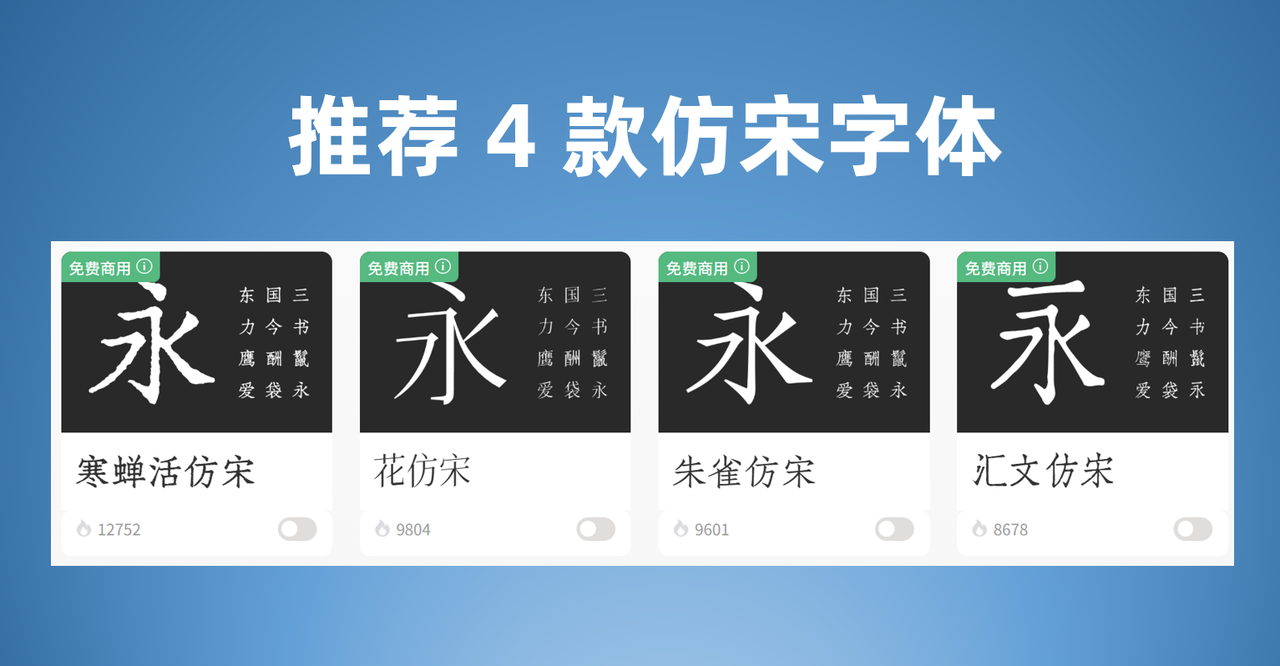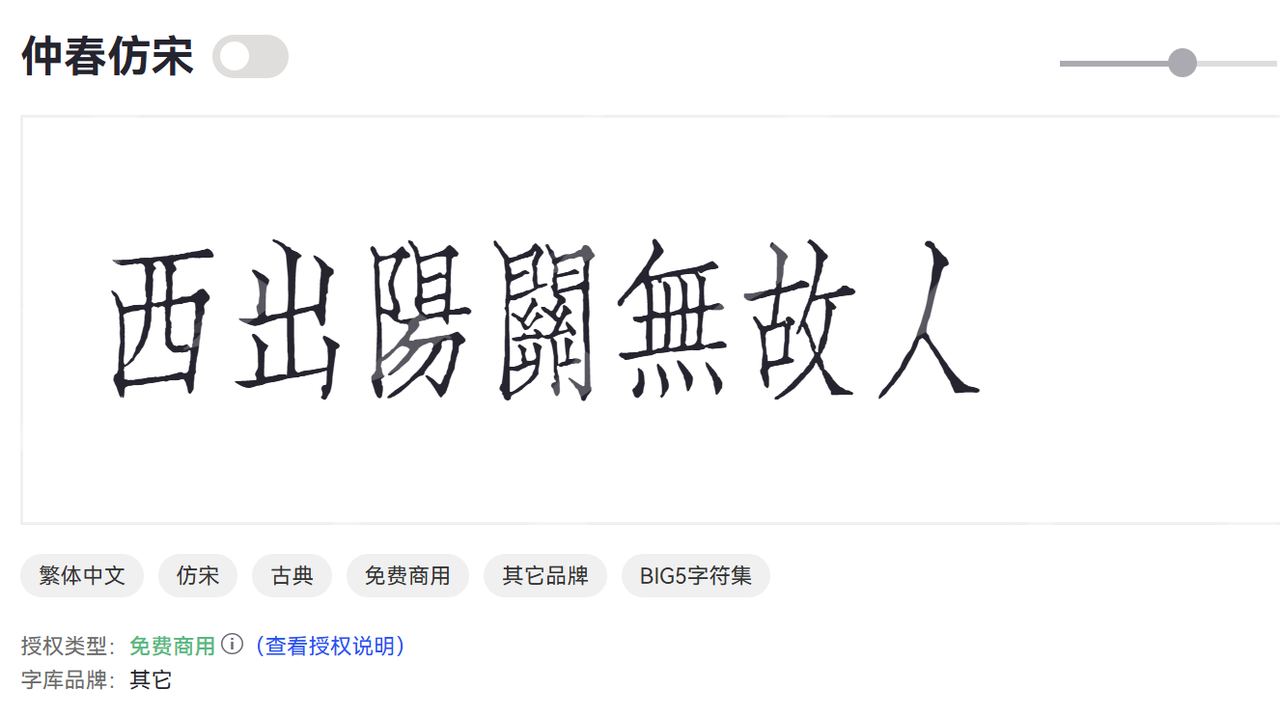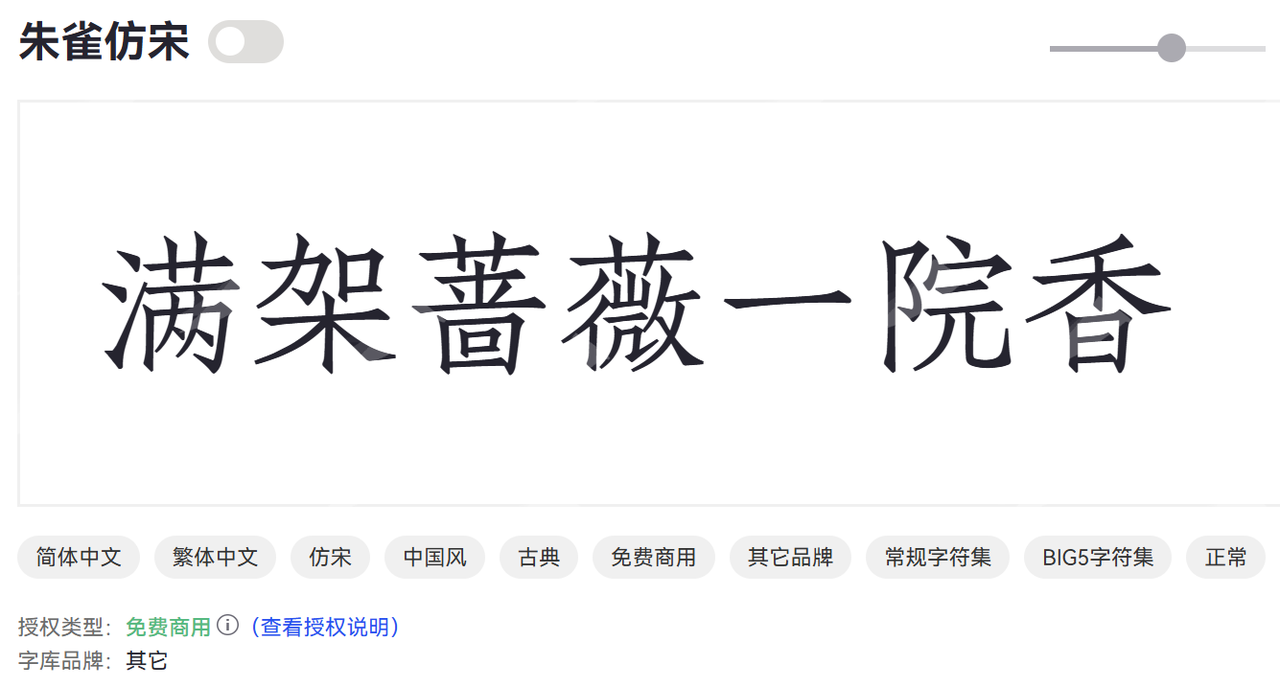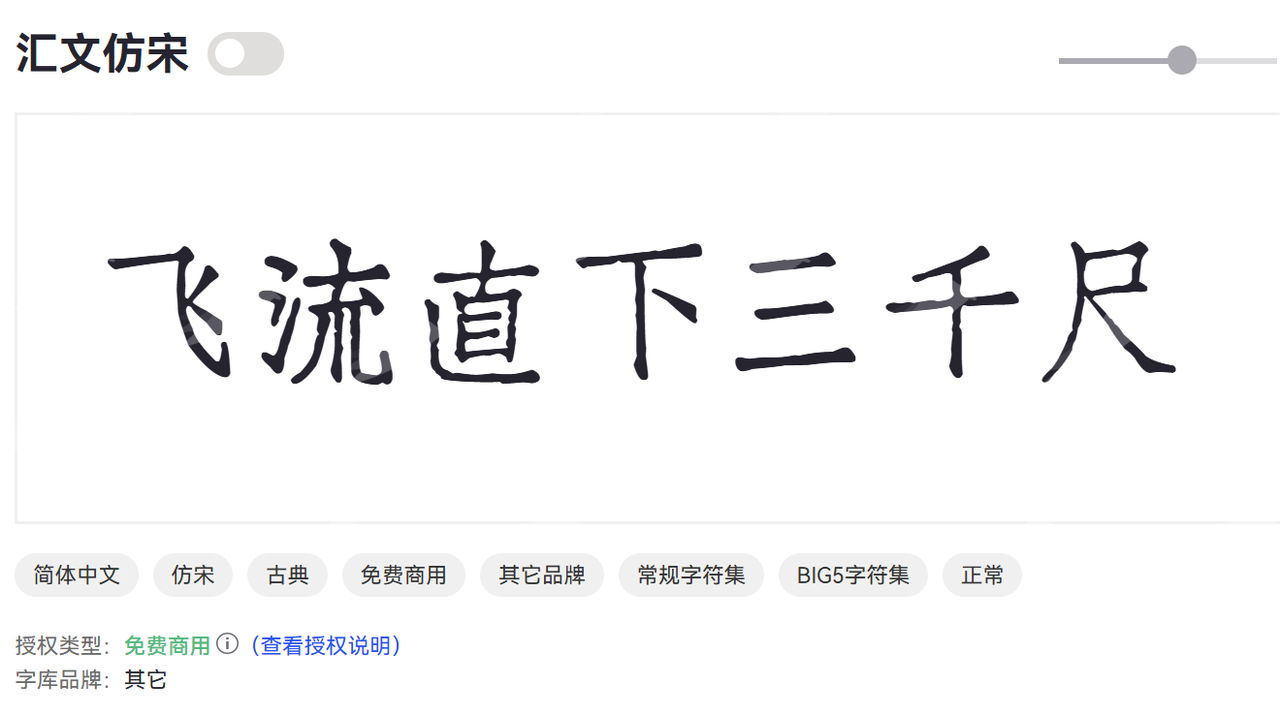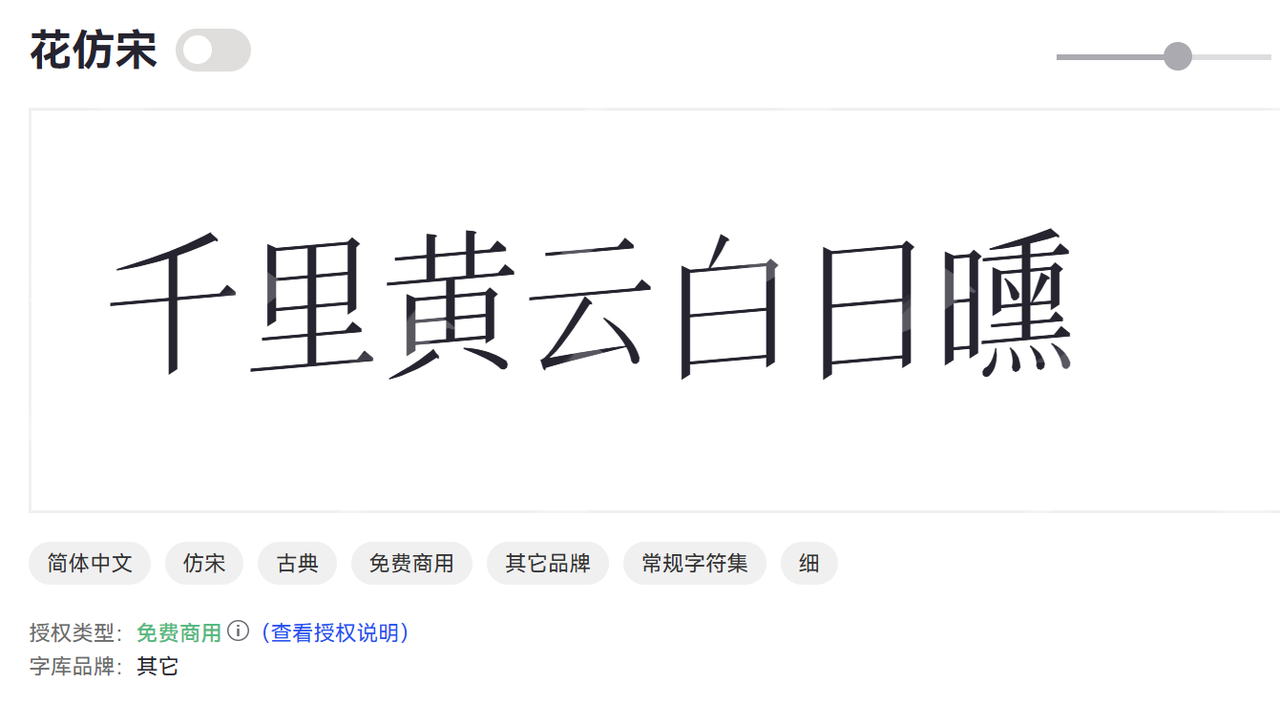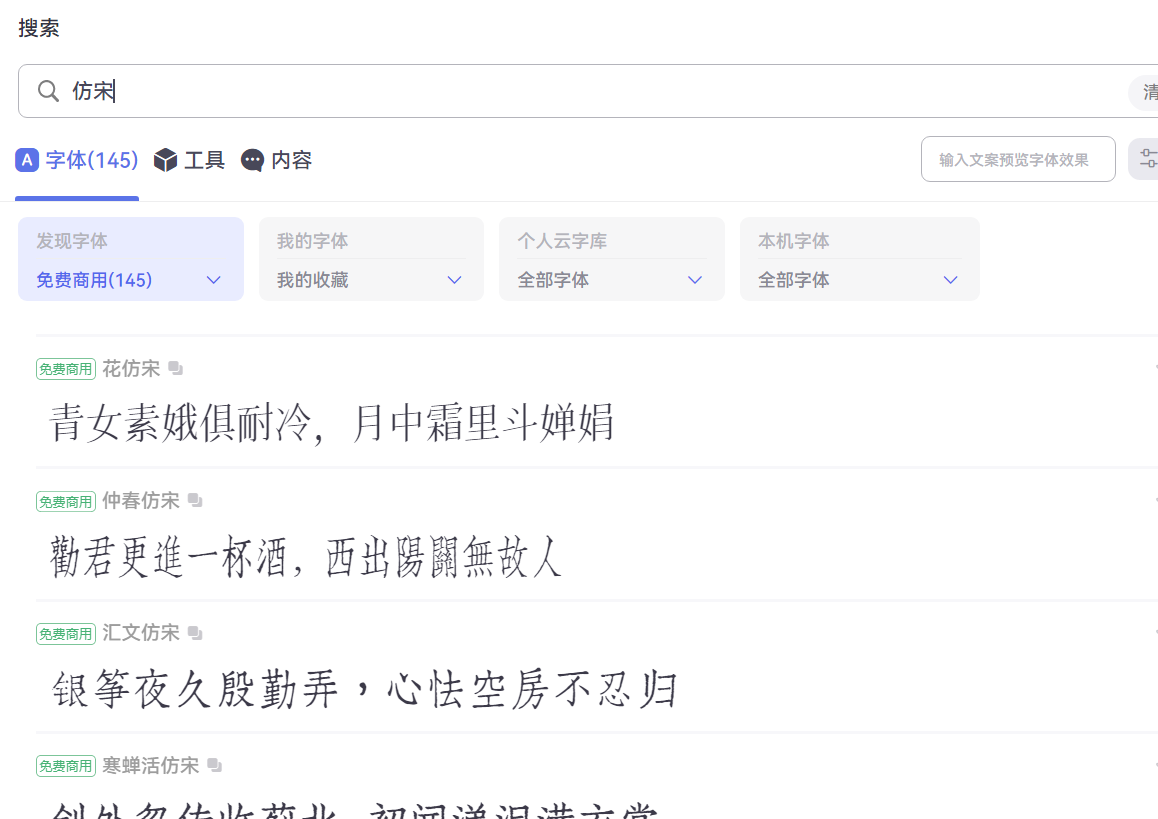
仿宋可以商用吗?5 款可以免费商用的仿宋字体
仿宋字体它不像黑体那样直接,也不像宋体那样方正古典,更不像楷体那样挥洒自如,仿宋体自有它一份独特的优雅和风骨。但是大多的仿宋是不可以商用的,本文我会重点给大家介绍 5 款可以免费商用的仿宋字体,同时会告诉大家一些实用的字体管理方法。
仿宋是一款什么字体
顾名思义,“仿宋”就是“仿照宋体”的意思,仿宋体借鉴了宋代刻本的风格,并将其标准化、规范化,使其既有宋代刻本的古朴典雅,又兼具现代印刷的清晰易读。
仿宋字体笔画粗细适中且相对均匀,与宋体那种横细竖粗、有明显衬线的特点不同,仿宋体的笔画粗细变化相对较小,视觉上更加柔和、统一。仿宋字体结构端正,重心平稳: 整体字形端庄大气,重心平稳,给人一种沉稳、正式的感觉。
5 款可以免费商用的仿宋字体
如果你对字体没有特别多的要求,只想找一款仿宋字体,本文就给你推荐 5 款可以免费商用的字体。
1. 仲春仿宋
仲春仿宋是一款植根于经典仿宋体字形,并融入现代审美考量的优质字体。它继承了仿宋体结构严谨、笔画清晰的特点,同时在细节上进行优化,使得字形更加均衡、雅致。这款字体使用场景非常多,适配多个场景。
特点与优势:
• 完美结合了传统仿宋的韵味与现代设计的简洁
• 清晰的笔画结构和适中的字重,确保了在不同尺寸和媒介表现都非常的清晰可读
• 适合公文、书籍排版、学术论文、文化宣传资料、品牌标识以及各类正式场合的理想选择,能有效提升内容的专业度和美观度。
1. 朱雀仿宋
朱雀仿宋以中国传统神兽“朱雀”命名,表现其字体风格的尊贵与灵动。它在仿宋体的基础上,注入了更为精致和富有艺术感的细节设计。字形端庄大气,笔画在保持仿宋体骨架的同时,融入了独特的韵律感。我曾经在给一家公司做展览的海报设计时,就使用了这块字体,因为刚好是国潮类的展会,所以效果比较好。
特点与优势:
• 字形设计充满艺术美感,赋予内容高雅、尊贵的调性。
• 在标题和重点信息展示时,具有强大的视觉吸引力。
• 适用于高端品牌、文化机构、艺术展览、典礼邀请函等场合。
1. 汇文仿宋
字体简介: 汇文仿宋是一款注重实用性和普适性的仿宋字体。其设计旨在为各类文本内容提供稳定、清晰且易于阅读的解决方案。字体结构方正,笔画规范,字间距和行间距经过精心调校,确保了在大量文字排版时的舒适度。它如同其名,汇聚文化与文字,致力于成为文字传播的优质载体。
特点与优势:
• 笔画均匀,字形稳定,有效降低阅读疲劳,非常适合长时间阅读的文本,如教材、报刊、杂志。
• 兼顾了不同应用场景的需求,无论是印刷还是屏幕显示,都能保持干净清晰。
• 适用于教育出版、新闻媒体、企业报告、产品说明等需要准确、高效传达信息的领域。
1. 花仿宋
花仿宋是一款富有浪漫与柔美气息的仿宋字体。它在传统仿宋体的基础上,融入了更为柔和的曲线和细腻的笔触,字形如花朵般绽放,充满生机与美感。我个人非常喜欢这个字体,在给朋友设计婚礼邀请函的时候,我就选择了这个字体,整体风格清新、雅致,给人以温馨愉悦的视觉感受,是一款充满个性的装饰性仿宋。
特点与优势:
• 字体设计像花一样,温柔浪漫,非常适合表达温馨、浪漫的主题。
• 能够体现设计作品的艺术气息和女性化的魅力,使其更具吸引力。
• 广泛应用于婚礼请柬、时尚杂志、美妆产品包装、女性品牌、贺卡、诗歌排版等领域。
1. 寒蝉活仿宋
寒蝉活仿宋打破了传统仿宋的刻板印象,笔画在保持基本规范的同时,融入了更为灵动和不拘一格的细节处理。字形结构可能略带手写感或非对称性,赋予字体一种生动、自然的生命力。比较适合一些艺术创意类的场景,目前我还没有实际使用过,但后面适合的场景一定会尝试。
特点与优势:
• 兼具仿宋的端庄与现代设计的灵动,具有强烈的辨识度。
• 适合在一些表达活泼、活力、突破的使用场景。
• 适用于文化创意产品、现代艺术展览、个人品牌、数字媒体内容以及需要注入个性和活力的设计项目。